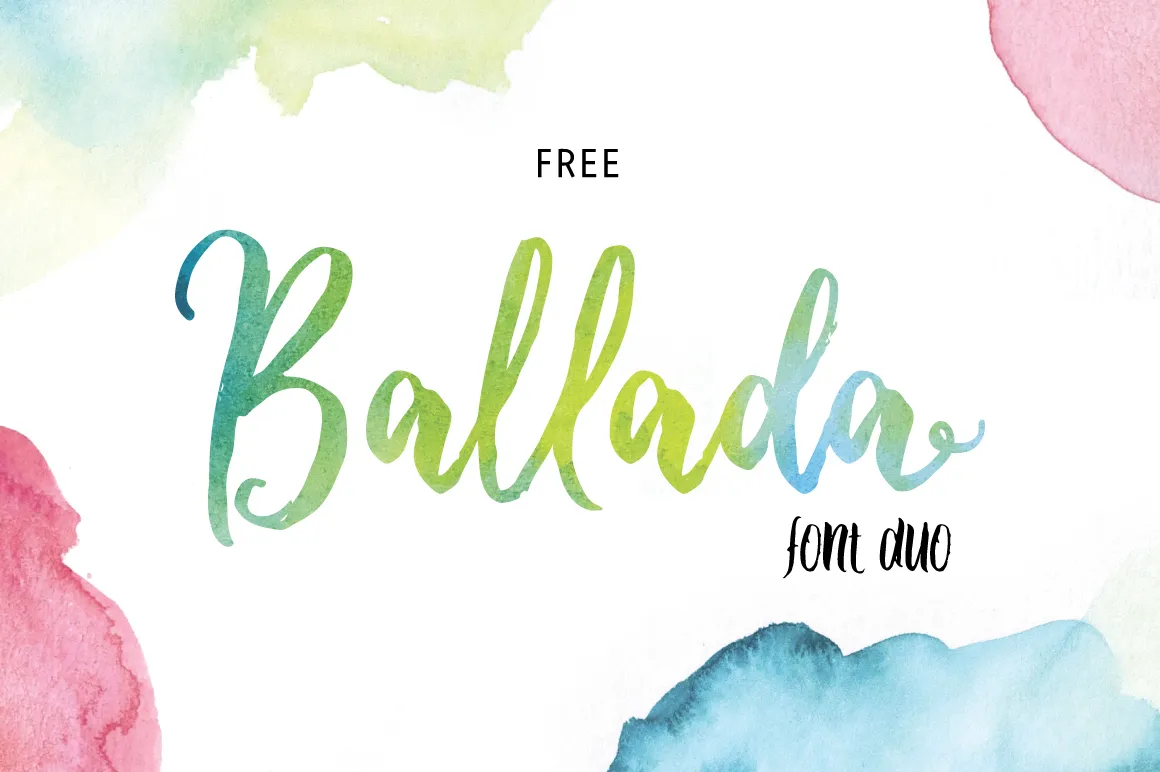
Ballada Brush Font
Estou aqui a descrição para a página de download da font “Ballada Brush Font”, idealizada para uma audiência atenta à estética visual e ao design: A “Ballada Brush Font” é um elegante tipo brush tipográfico que transmite sofisticação e originalidade. Desenhado pelo Pathero Studio, Ballada oferece a possibilidade de criar designs únicos e imprimíveis diretamente em seus projetos. Esta fonte ficará perfeitamente em sintonia com o estilo script Ballada, proporcionando resultados incrivelmente interessantes. Ideal para os desejos do design gráfico que valorizam elementos naturais como a pintura à mão livre ou letras artísticas fortes, como cabeçalhos de blogs, peças de arte, elementos de casamentos e adesivos, revestimentos de livros, cartões de convite, cards de empresas e presentes de nascimento. Além disso, ela é perfeita para aplicação em materiais impressos ou digitais, como letras apropriadas para t-shirts, roupas e outros produtos. A fonte Ballada Brush é perfeitamente adaptável para uso em qualquer formato visual que você possa imaginar, tornando-a uma opção versátil para designers de diferentes estilos. Com ela na sua coleção, é fácil criar design único, que expressará a personalidade e o estilo específico do seu projeto.